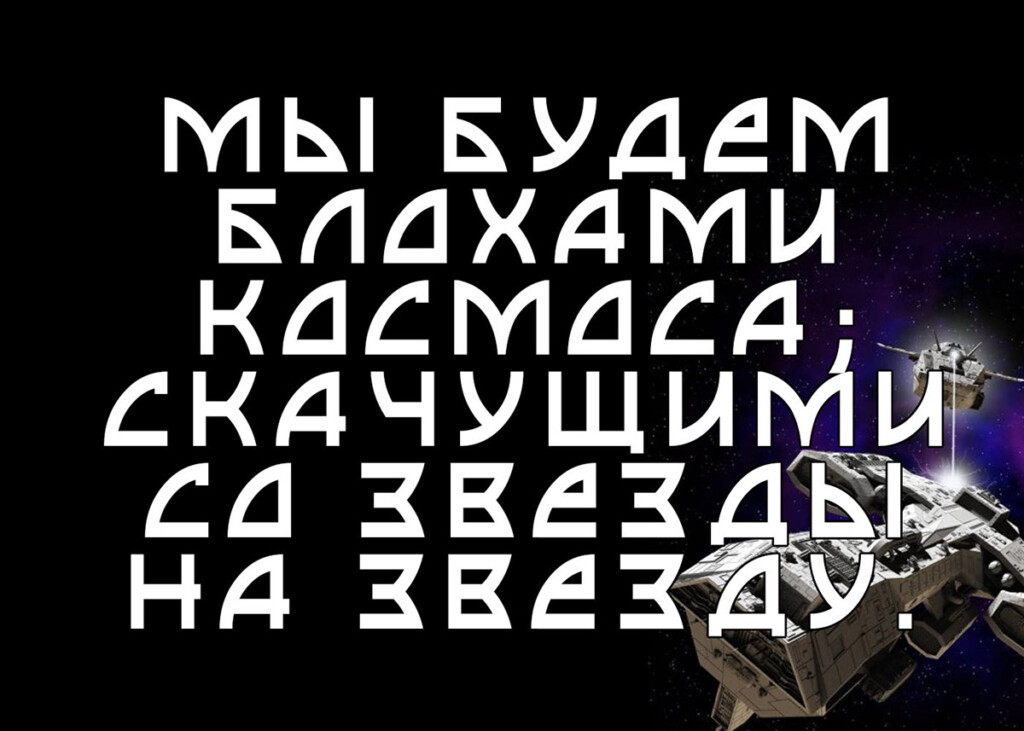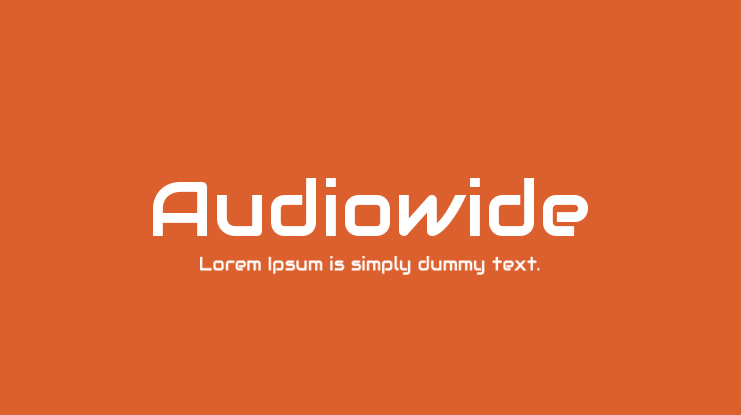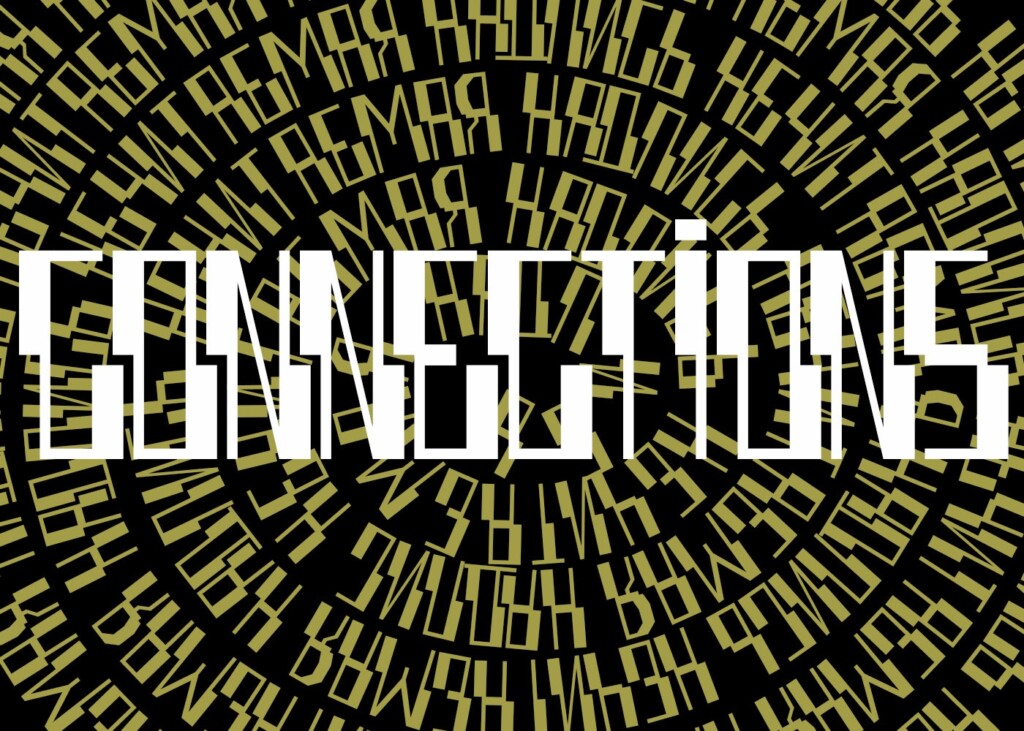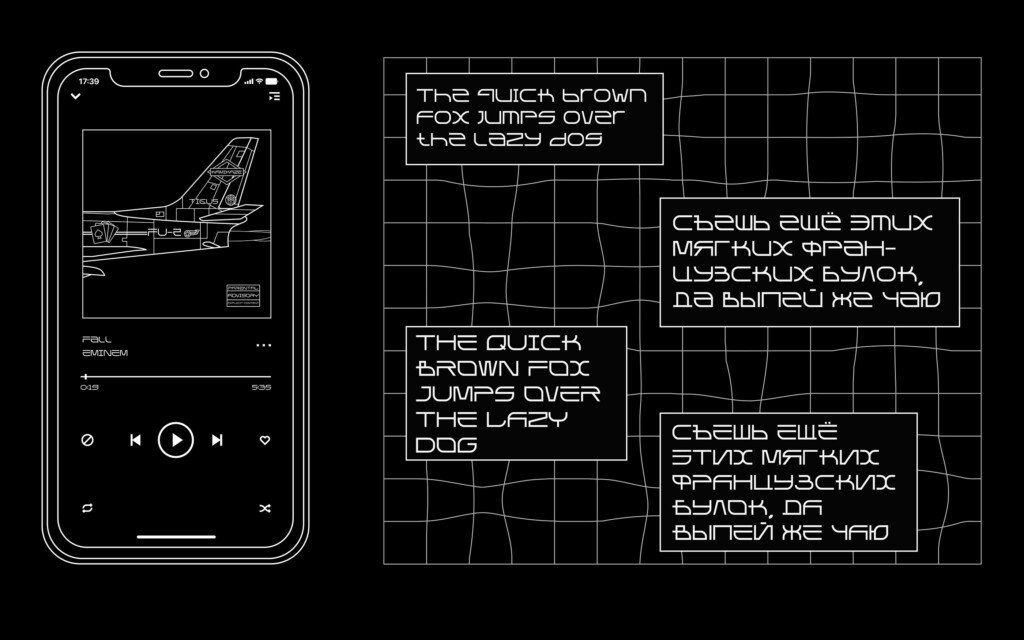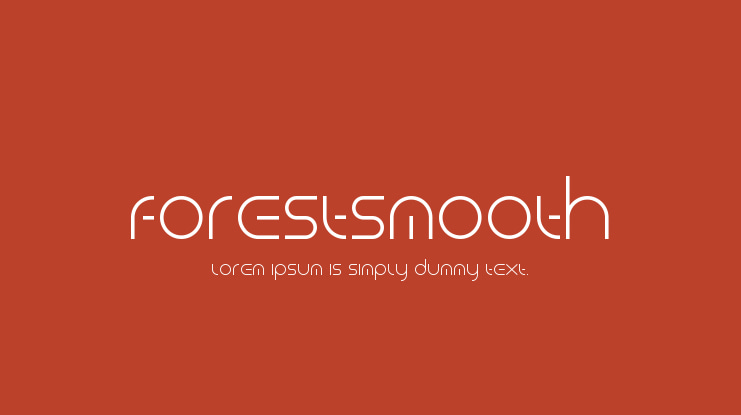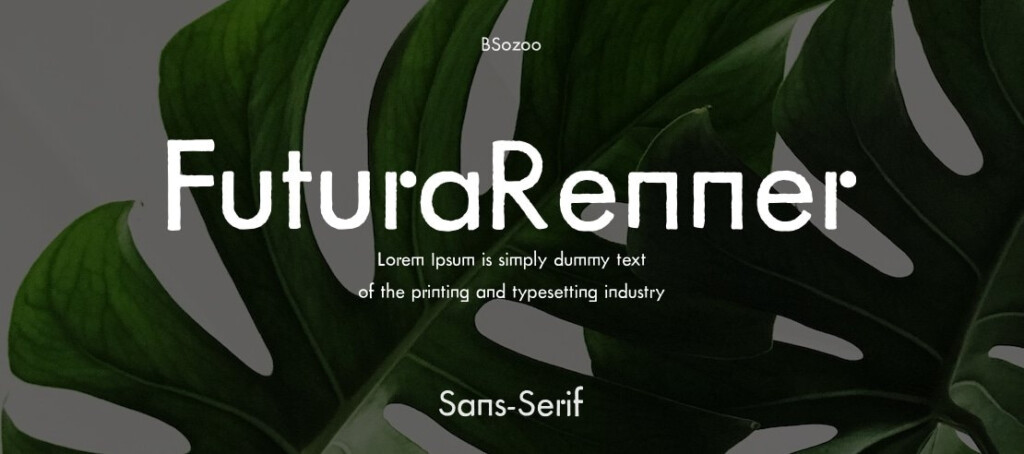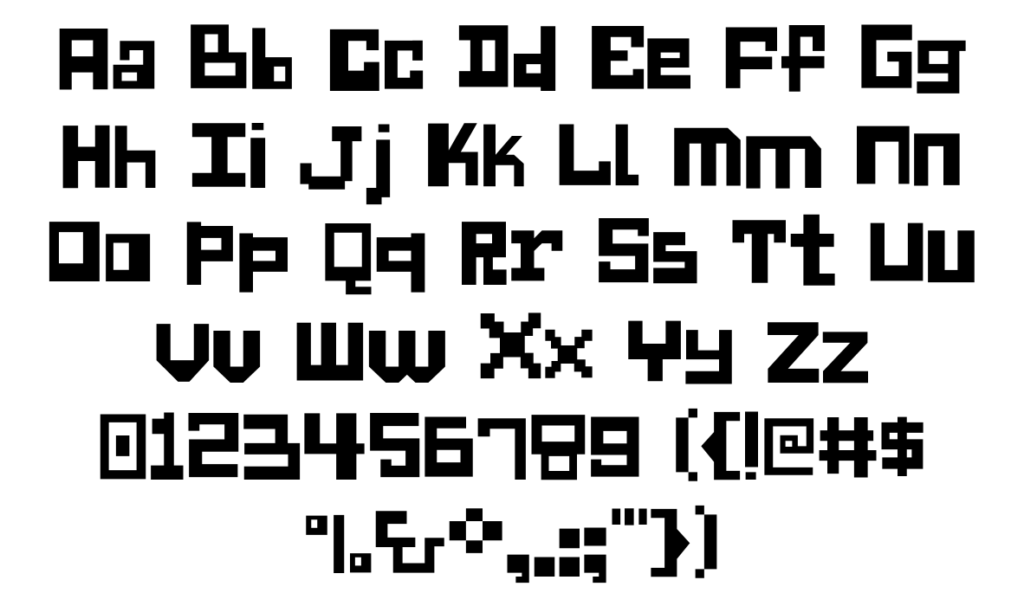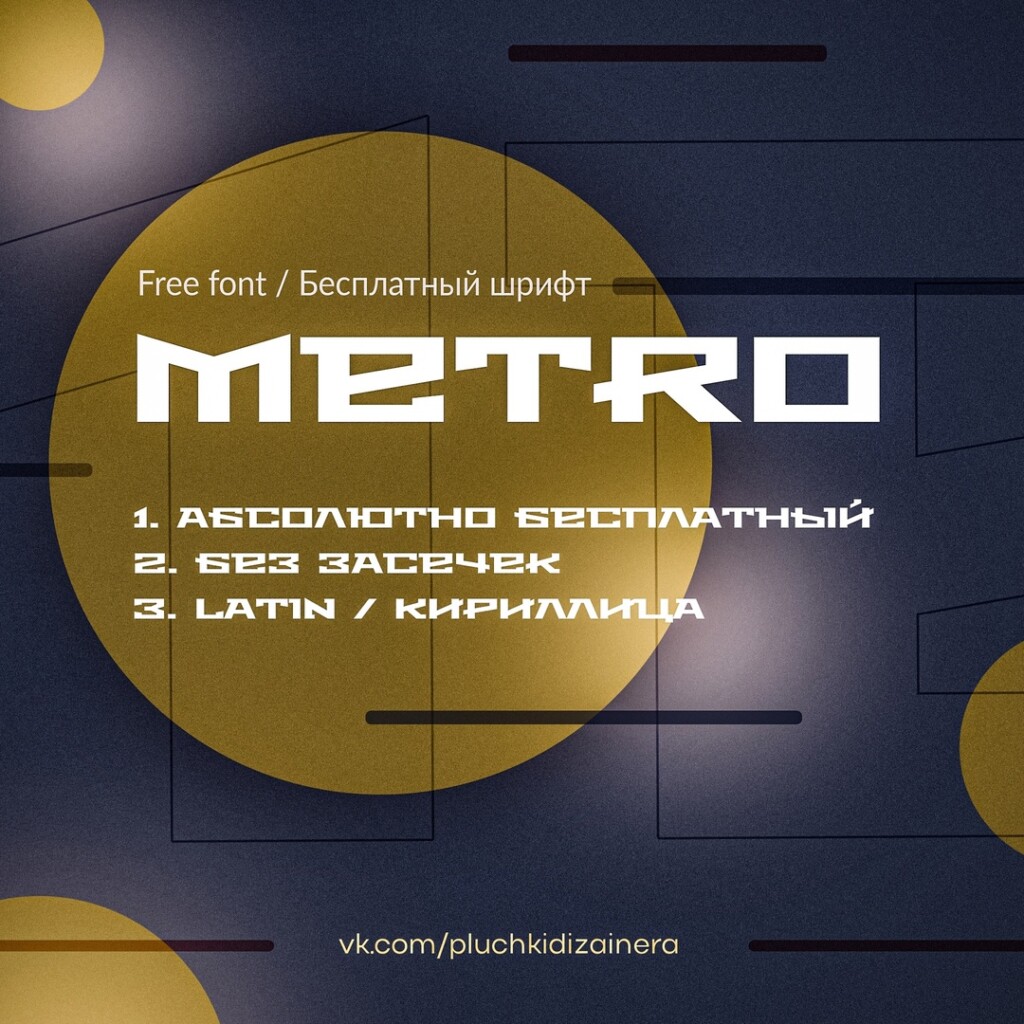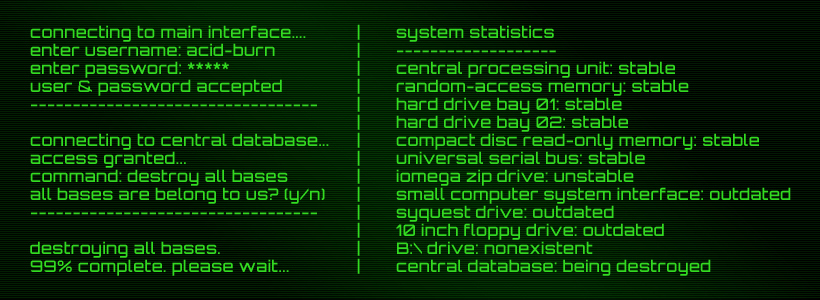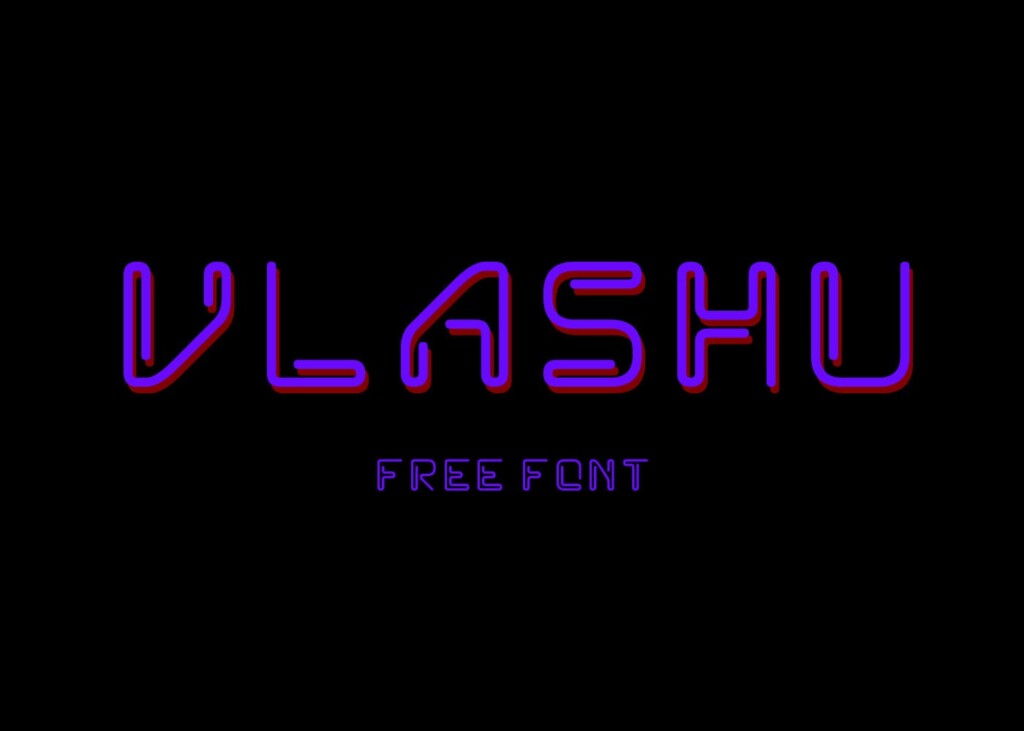
Бесплатные футуристичные шрифты: топ-10
Визуальный язык будущего — это острые формы, техногенные изгибы и холодная эстетика прогресса. Современный дизайн всё больше стремится к минимализму, технологичности и смелости, и шрифт здесь играет ключевую роль. Мы собрали подборку бесплатных футуристичных гарнитур, чтобы твои проекты выглядели так, будто их верстали на борту «Энтерпрайза». Эти шрифты идеально впишутся в digital-среду, интерфейсы и брендинг инновационных компаний. Будущее уже здесь — и у него свой алфавит.
Футуристичные шрифты кириллица
Футуристичные шрифты с поддержкой кириллических символов — это отличное решение для проектов, где важна современная эстетика и технологичный стиль. Большинство таких шрифтов подходят в основном для заголовков, поскольку у многих из них необычные формы букв, что делает чтение основного текста затруднительным. Тем не менее, футуристичный шрифт может добавить визуальную выразительность и технологичный акцент.
Используй шрифтовые пары: сочетай футуристичный шрифт для заголовков и простой для основного текста. Это сделает дизайн гармоничным и удобным для восприятия
Что делает шрифт футуристичным? Это использование геометрических форм, острых углов, необычных пропорций и линий, которые создают ощущение современности и прогресса. Такие элементы придают шрифту динамичность, индивидуальность и особую визуальную привлекательность, подходящую для инновационных и смелых дизайнерских решений.
DaMiOne
DaMiOne — футуристический шрифт с чёткой геометрией и выразительным sci-fi-стилем. Он подходит для заголовков, постеров, интерфейсов, digital-графики. Особенно эффектно смотрится в тематиках, связанных с инновационными проектами, технологиями будущего и виртуальной реальностью. DaMiOne помогает создать атмосферу прогресса и высокотехнологичного будущего. Кириллица есть.
ForestSmooth
ForestSmooth — это шрифт с необычным контрастом: в нём сочетаются природные мягкие линии и графика футуристических форм. Он выглядит свежо и нестандартно, идеально подходя для дизайн-проектов, где важна оригинальность. ForestSmooth хорошо работает в заголовках, афишах и интерфейсах, особенно в проектах, где пересекаются темы природы, технологий и современного визуального стиля. Кириллица есть.
Futura Renner
Futura Renner — интересный минималистичный гротеск. Классическая шрифт Futura претерпел некоторые изменения: буква «n» теперь используется русская печатная «п», а вместо штриха в букве «r» — точка.
Несмотря на это, Futura Renner комфортен для чтения и идеально подходит не только для заголовков, но и для основного текста. Этот шрифт не поддерживает кириллицу, но его универсальность и стиль делают Futura Renner отличным выбором для множества современных проектов.
Kappa's Pororoca
Kappa’s Pororoca — экспериментальный шрифт, как будто написанный рукой пришельца. Со своими нестандартными формами и выразительной динамикой он идеально подходит для bold-дизайна и эксцентричных проектов. Он привлекает внимание с первого взгляда и отлично вписывается в графику, где важны провокация, энергия и визуальная дерзость. Кириллица есть.
Arounder
Arounder — футуристический шрифт с плавной геометрией и закруглёнными формами, навеянный эстетикой цифровых интерфейсов. Современный, гладкий и читаемый, он идеально подходит для айдентики, футуристичных сайтов, digital-обложек и sci-fi-графики. Arounder задаёт чистый, продуманный ритм и придаёт дизайну ощущение технологичного будущего. Кириллица есть.
Сonnections and Order
Connections and Order — нестандартный шрифт, вдохновлённый модульной сеткой, логикой схем и архитектурой данных. Он резкий, рваный, урбанистичный. За счёт особенной формы букв он менее читаемый, поэтому Connections and Order лучше использовать точечно: в крупных заголовках, акцентах, арт-плакатах и визуальных инсталляциях. Большой кегль и продуманная композиция помогут раскрыть его дерзкий и технологичный характер. Кириллица есть.
Metro
Metro — шрифт с остроугольной геометрией и современным индустриальным стилем. Широкий по конструкции, он занимает много пространства и идеально подходит для заголовков. Metro отлично работает в крупных размерах, в интерфейсах, на постерах и в любой графике, где необходимо сделать акцент на современной, сильной визуальной идентичности. Кириллица есть.
3. Учитывай читабельность: особенно если шрифт используется в интерфейсах или презентациях.
5. Тестируй в макете: один и тот же шрифт может выглядеть по-разному в зависимости от сетки, цвета и фона.
Выбирай гарнитуру, которая резонирует с идеей твоего дизайна — будь то digital-интерфейс, sci-fi айдентика или презентация стартапа. Не бойся экспериментировать: будущее любит смелых.